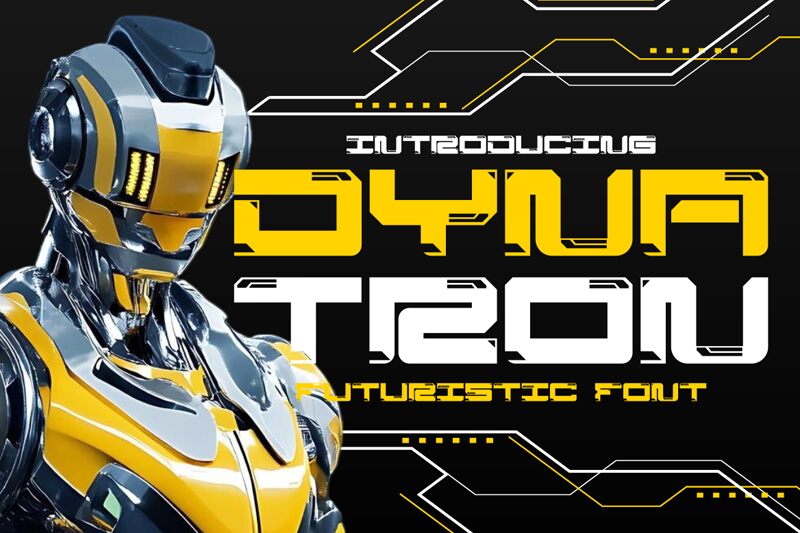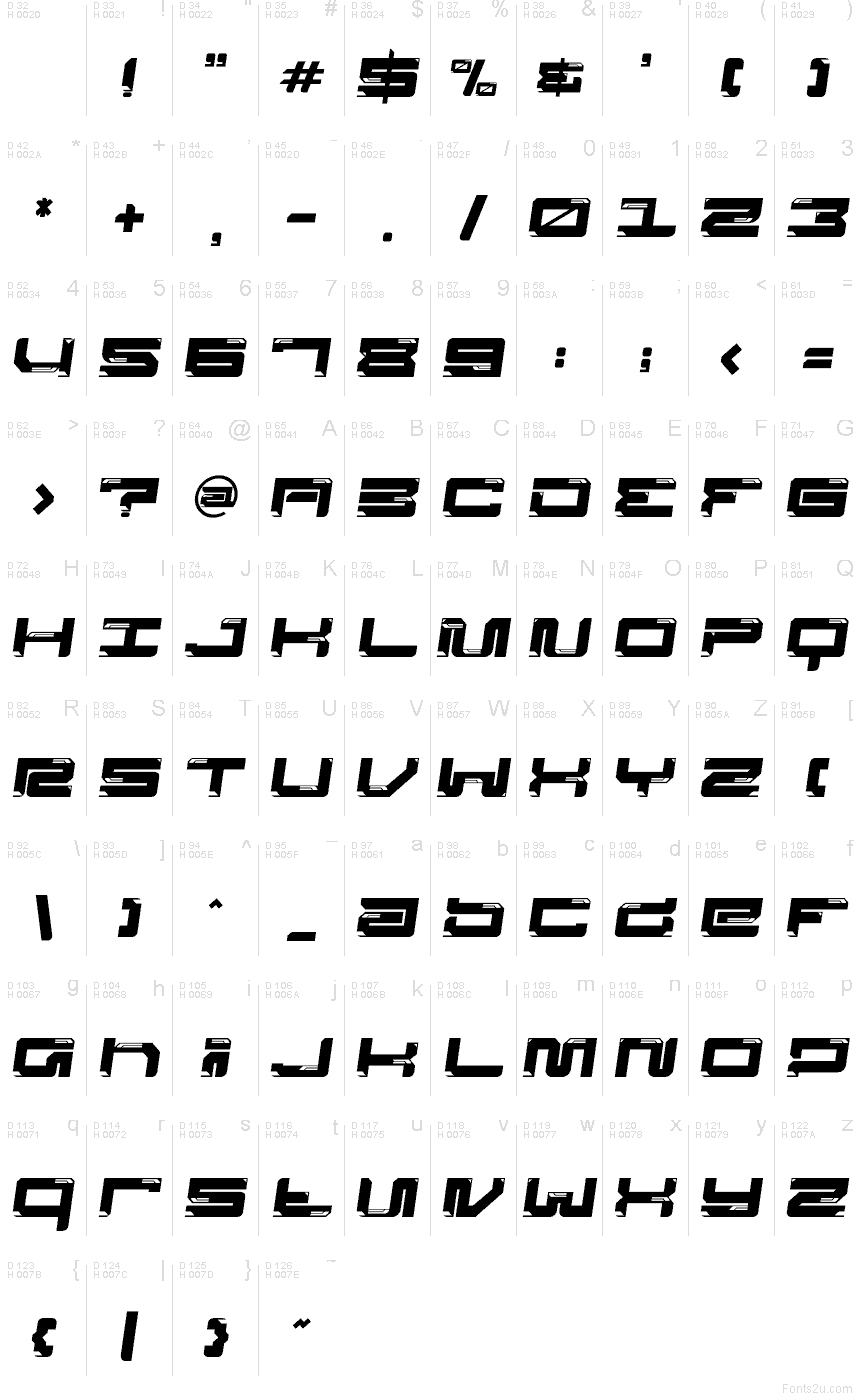
Shanaf StudioによるDynatron Slantは、コンセプトカーのようなスピード感あふれる、無料のフューチャリスティックなディスプレイフォントです。大きく大胆な形状、切り落とされた角、そして通気口やパネルラインを思わせる繊細なラインの切り込みが、デザイン全体に近未来的なSFハードウェアのような雰囲気を与えています。
ゲームロゴ、テックイベントのポスター、アルバムジャケット、タイトルカード、eスポーツのブランディングなど、短い単語でその角張ったリズムを活かすデザインに最適です。無料フォントでありながら、UIのヘッドラインやパッケージデザインなど、冷たいミニマリズムに陥ることなく、合成的でメカニカルな声を必要とする場面で活躍します。
Dynatron Slantフォントの紹介と見本
Dynatron Slantフォントの文字一覧
Dynatron Slantの文字一覧:基本ラテン文字、1ページ目
Dynatron Slantフォントのグリフ — 基本ラテン文字、1ページ目